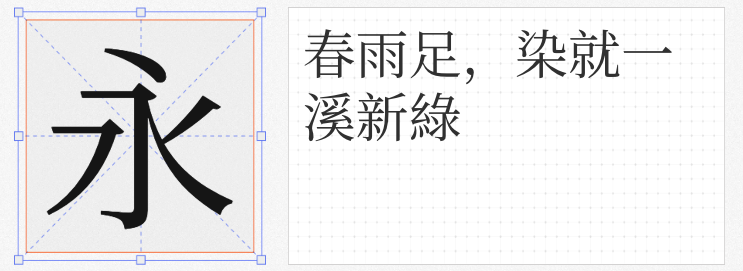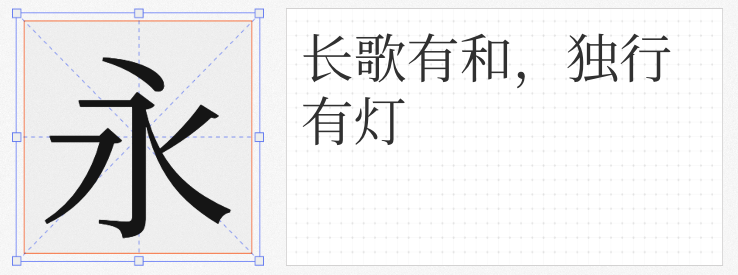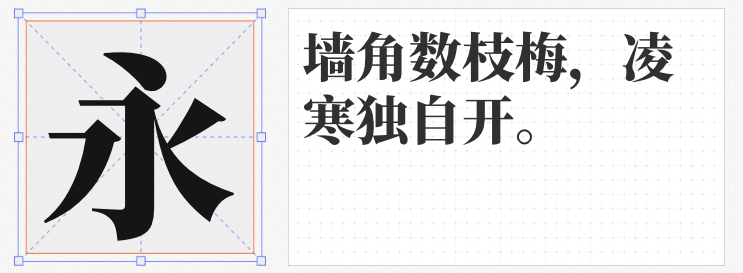
在追求视觉效率与文化表达的平衡中,宋体以其独特的笔画结构与人文气质,成为中文设计领域的经典选择。以下四款免费商用宋体,不仅延续了传统书法的韵味,更通过现代技术优化了多场景适用性,为设计师提供零成本的高品质解决方案。
作为Adobe与谷歌联合开发的泛CJK字体家族成员,思源宋体以跨语言支持为核心优势。其字形结构融合中日韩越审美特征,简体中文部分严格遵循大陆字形标准,同时覆盖拉丁语、希腊语等西文字符。粗重字重赋予标题强烈的视觉穿透力,而细腻的衬线处理又保留了宋体的典雅气质,适用于品牌主视觉、文化类海报等需要国际传播的场景。
2. 香萃等粗宋
这款专为屏幕显示优化的宋体,通过调整横竖比例与笔画曲率,在数字媒介中呈现出纸媒般的温润质感。中宫收紧的设计提升了小字号下的识别度,而柔和的转角处理则消解了传统宋体的严肃感。无论是移动端界面还是电子书排版,其平静温暖的气质都能营造舒适的阅读体验,成为新媒体内容设计的理想选择。
3. 源古宋体
基于古籍印刷规范改造的特殊字体,源古宋体完整保留了《古籍印刷通用字规范》中的异体字形。通过整合思源宋体与文津馆古籍字库,设计师可精准还原历史文献的视觉风貌。这款字体特别适合传统文化展览、古籍数字化等需要学术严谨性的项目,让现代设计承载千年文脉。
4. 文津宋体
作为目前最完整的开源宋体大字符集解决方案,文津宋体通过GlyphWiki数据与定制引擎,实现了Unicode与IVD注册字形的全覆盖。其简体中文形态严格遵循国家标准,2.8万汉字容量满足从古籍修复到现代出版的一切需求。OFL开源协议赋予设计师绝对的使用自由,堪称专业领域不可或缺的基础字库。
这四款字体通过技术革新与文化深耕,重新定义了免费商用字体的价值边界。无论是商业项目还是文化创作,它们都能以零成本提供专业级的视觉表达,让设计在传承与创新间找到完美支点。